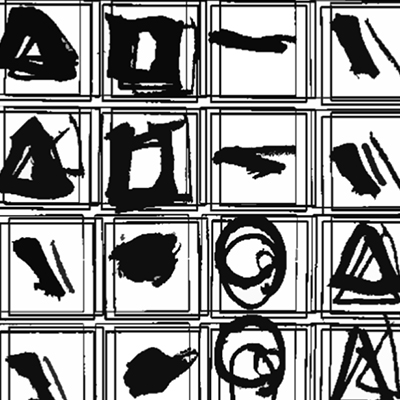
○△□ 01分別
Artist串原理栄
Designer上栗 優紀
Organizationむつみ工房
まる さんかく しかく。無機的なモチーフがチカラ強く描かれた、コミカルながらもハードボイルドでシンプルなデザイン。区別して分かたれること。(上栗 優紀)
シンプルなモチーフからフォントが作れないか、と描いて貰いましたがこれはこれで面白いではないですか!(むつみ工房)